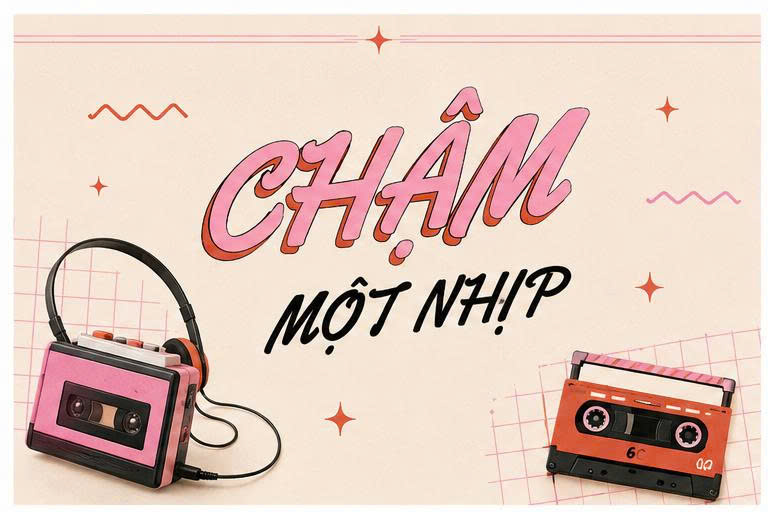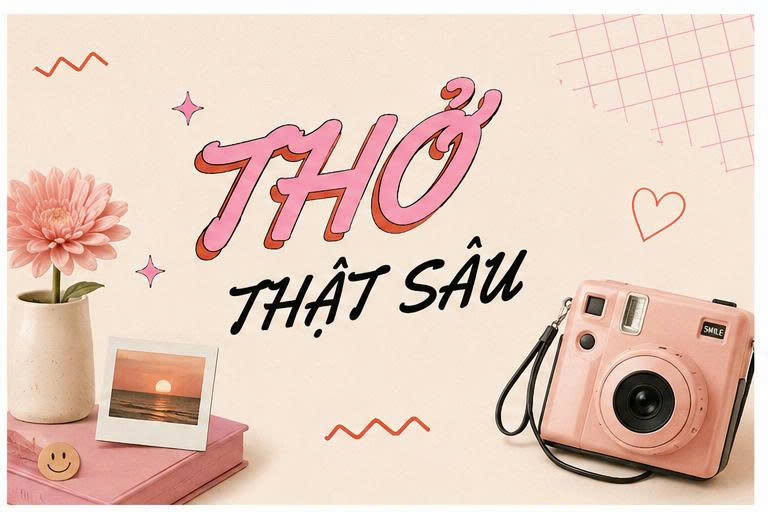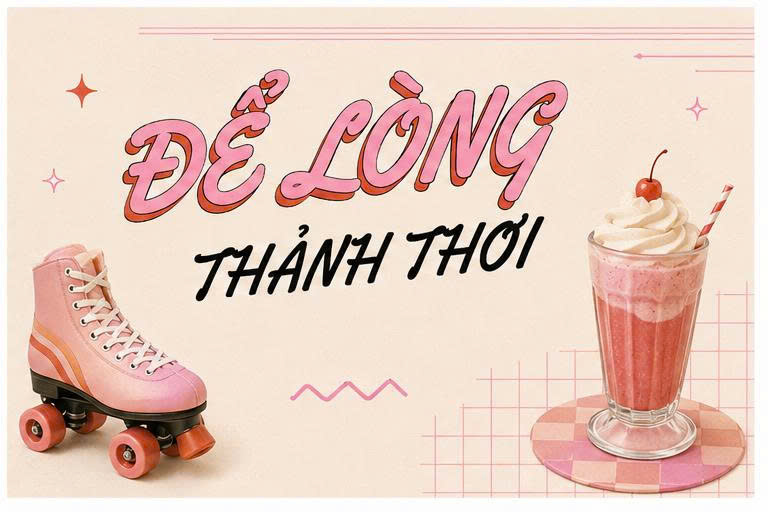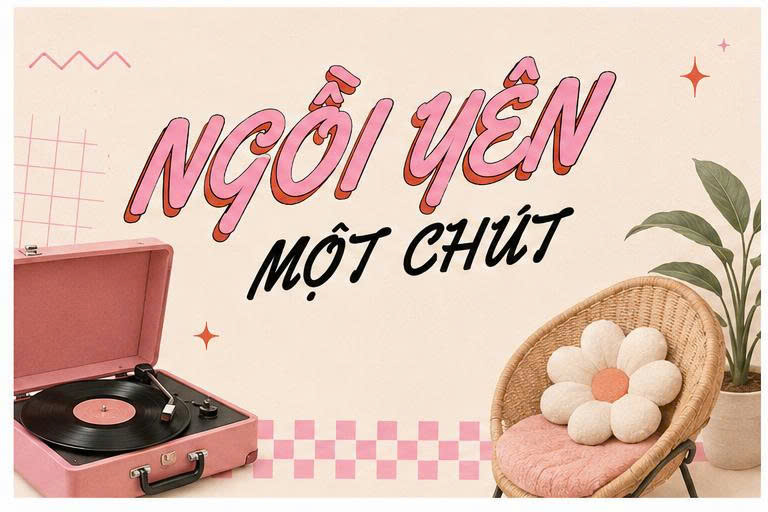
Font Việt hóa Yellowtail là bộ phông chữ thuộc dòng Brush Script mang phong cách cổ điển (Vintage), được thiết kế bởi Astigmatic lấy cảm hứng từ các kiểu chữ quảng cáo thập niên 1930. Với những đường nét mô phỏng nét cọ vẽ bản dẹt, nghiêng một góc tinh tế và đầy sự phóng khoáng, Yellowtail là lựa chọn tuyệt vời cho các thiết kế logo, tiêu đề bao bì sản phẩm mang hơi hướng Retro. Doozypack.vn cung cấp link tải font Yellowtail chuẩn, giúp bạn sở hữu bộ font Yellowtail Việt hóa không lỗi dấu để hiện thực hóa các ý tưởng thiết kế đậm chất nghệ thuật.
Đặc điểm thẩm mỹ độc đáo của font Yellowtail Việt hóa
Yellowtail không chỉ đơn thuần là một phông chữ viết tay; nó là sự kết hợp khéo léo giữa cấu trúc chữ Script truyền thống và nhịp điệu của đồ họa hiện đại.
Phong cách Brush Script phóng khoáng và tự nhiên
Đặc trưng lớn nhất của font Việt hóa Yellowtail là các nét chữ có độ dày không đồng đều, mô phỏng lại áp lực đưa bút lông trên bề mặt giấy. Các ký tự được thiết kế với độ nghiêng đồng nhất về bên phải, tạo cảm giác chuyển động và tràn đầy năng lượng. Điểm thú vị của Yellowtail là sự pha trộn giữa các chữ cái có nét nối và không có nét nối, mang lại vẻ ngoài tự nhiên như một bản viết tay thực thụ.
Hệ thống dấu tiếng Việt được tinh chỉnh hài hòa
Nỗi đau của các designer khi sử dụng font Yellowtail bản gốc là các bộ dấu tiếng Việt thường bị nhảy font hoặc không cân đối với thân chữ vốn mang tính trang trí cao. Phiên bản Việt hóa tại Doozypack.vn đã được tối ưu hoàn toàn. Các dấu thanh (sắc, huyền, hỏi, ngã, nặng) được đặt ở vị trí cân đối, hài hòa với độ Bold của nét cọ, đảm bảo văn bản tiếng Việt luôn giữ được sự thanh thoát và chuyên nghiệp.
Tại sao designer nên download font Yellowtail cho thiết kế bao bì?
Trong ngành thiết kế và sản xuất bao bì tại Doozypack.vn, Yellowtail thường xuyên được ưu tiên cho các dự án cần tạo điểm nhấn hoài cổ:
- Tạo dấu ấn Vintage chuyên nghiệp: Yellowtail giúp bao bì sản phẩm của bạn toát lên vẻ lâu đời và uy tín, đặc biệt phù hợp cho ngành cà phê, thực phẩm truyền thống và tiệm bánh.
- Khả năng nhận diện cực tốt: Nhờ nét chữ dày dặn và cá tính, tên thương hiệu in bằng font Yellowtail nổi bật hoàn toàn trên kệ hàng, thu hút sự chú ý của khách hàng ngay từ cái nhìn đầu tiên.
- Tính ứng dụng đa dạng: Bạn có thể dùng font này cho cả nhãn dán chai lọ, vỏ hộp quà tặng hay các banner quảng cáo mạng xã hội phong cách Retro.